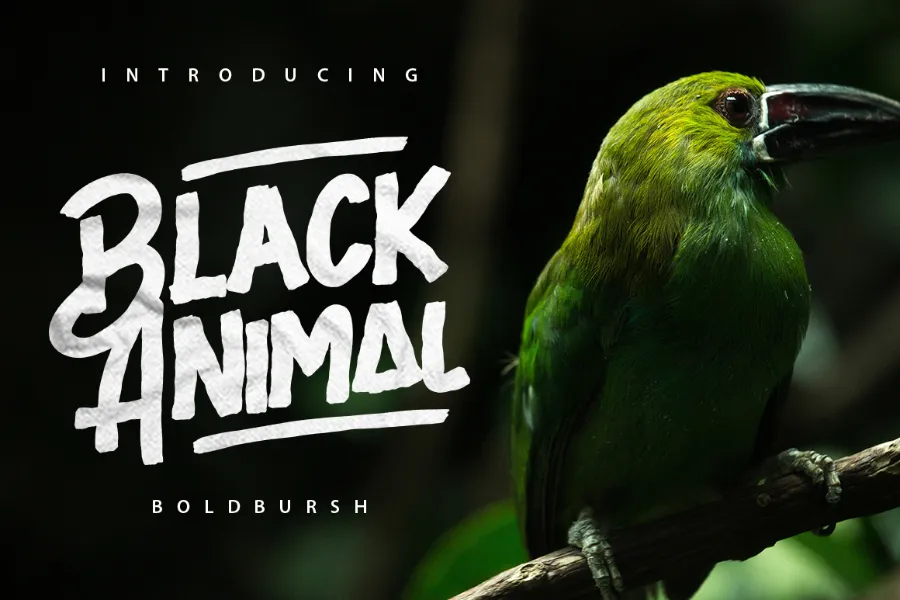
Black Animal Font – Download Grátis
Introduzimos Black Animal Font para quem busca uma solução visual única para projetos digitais. Desenhada por Hamilton, essa fonte brush estilo é perfeita para criar design exuberante e único. Obrigado a sizimon pelo desenvolvimento desta fonte. Ideal tanto para logotipos quanto para nome tag, Black Animal convida ao uso de citações escritas à mão, embalagens de produtos, mercadorias, mídias sociais e cartões de agradecimento. É especialmente adequada aos que desejam economizar tempo na criação de design para produtos, graças à sua vasta gama de caracteres maiúsculos e minúsculos, sinais gráficos amplamente disponíveis e suporte multilíngue. Estamos ansiosos para compartilhar a diversidade de aplicabilidade desta fonte brush, que vai adicionar um toque autêntico à sua próxima criação.